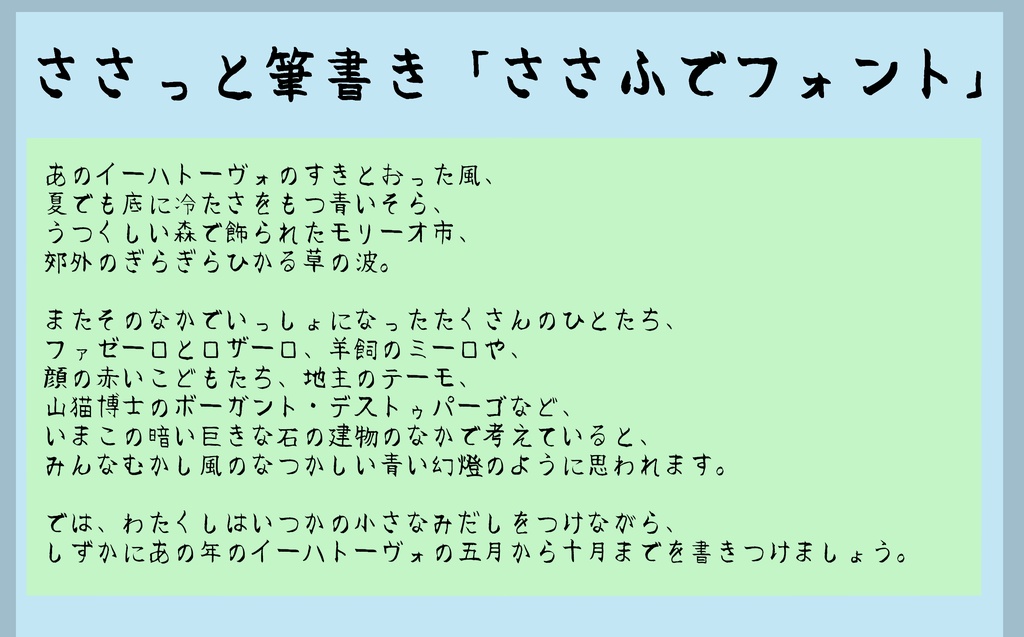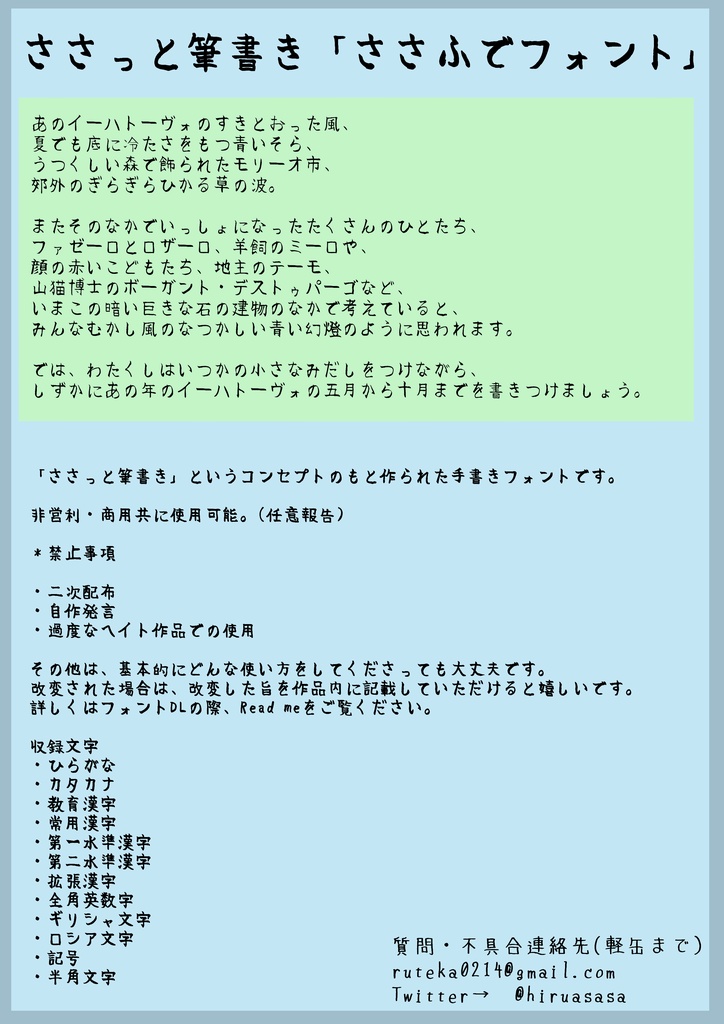
刺竹手写体字体信息
一种采用作者的手写笔迹制作的手写自由字体,采用TrueType格式。
[记录字符]
- 平假名
- 片假名
- 教育汉字
- 常用汉字
- 第一水准汉字
- 第二水准汉字
- 扩张汉字
- 全角英数字
- 希腊字母
- 俄文字母
- 记号
- 半角文字
“刺竹手写体”是一款书写很新颖的字体,字体大方,适合各种设计作品使用!欢迎下载!